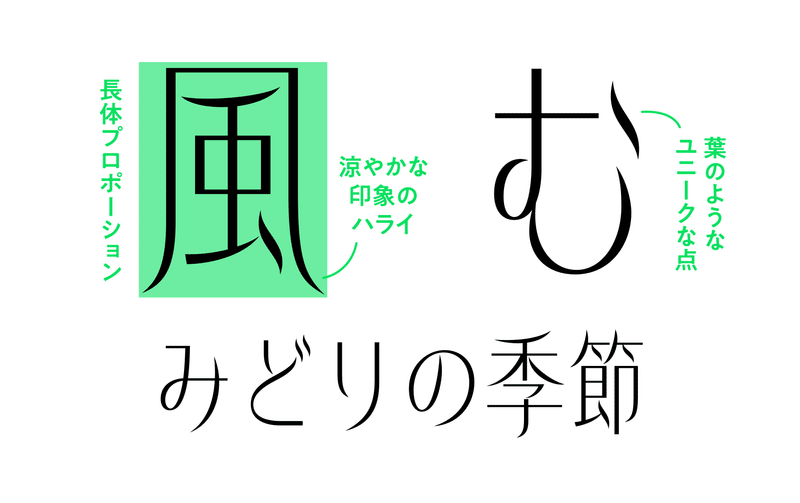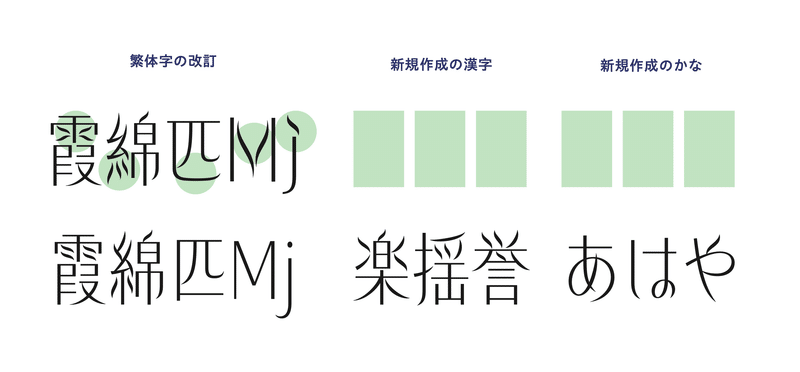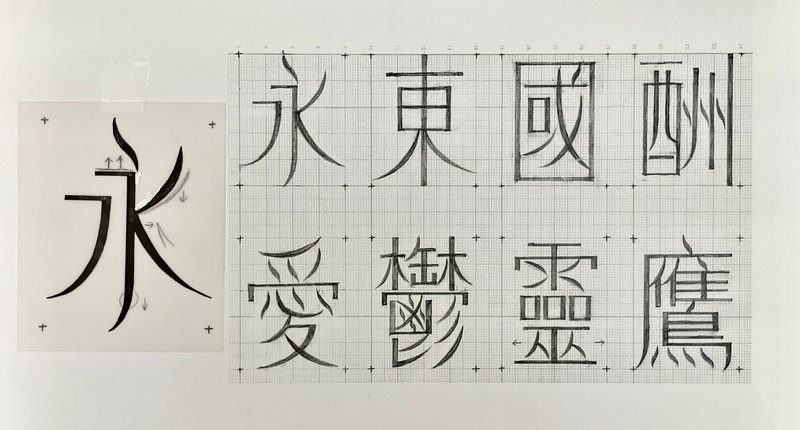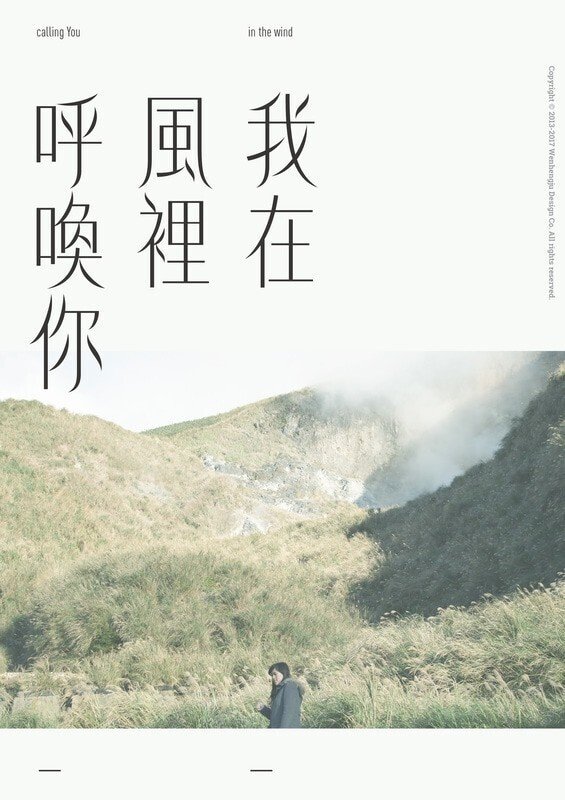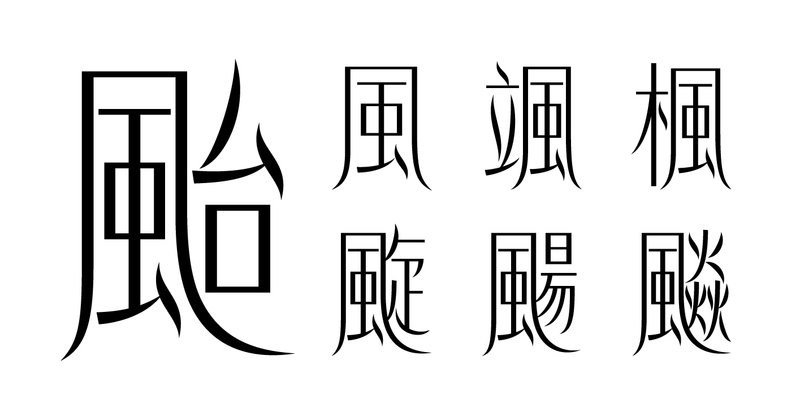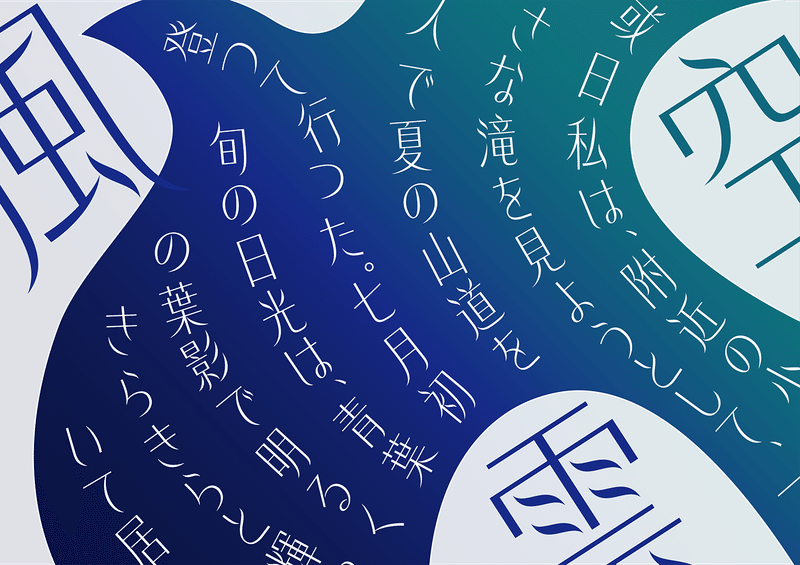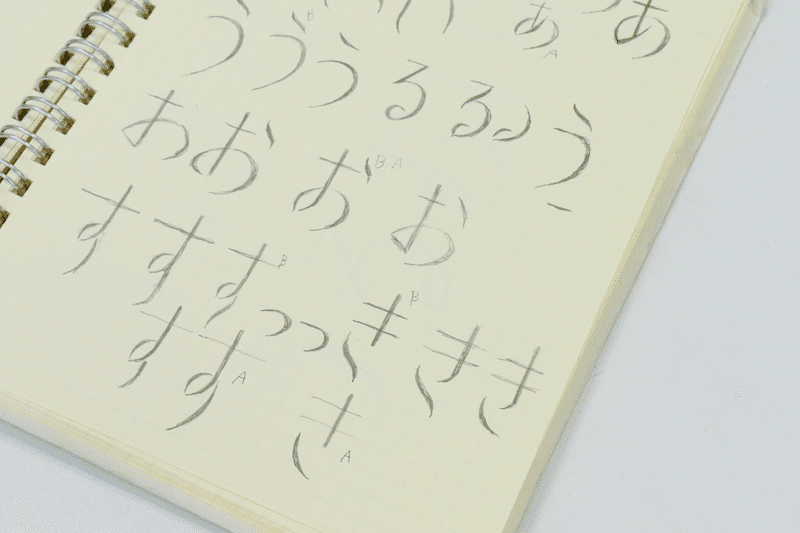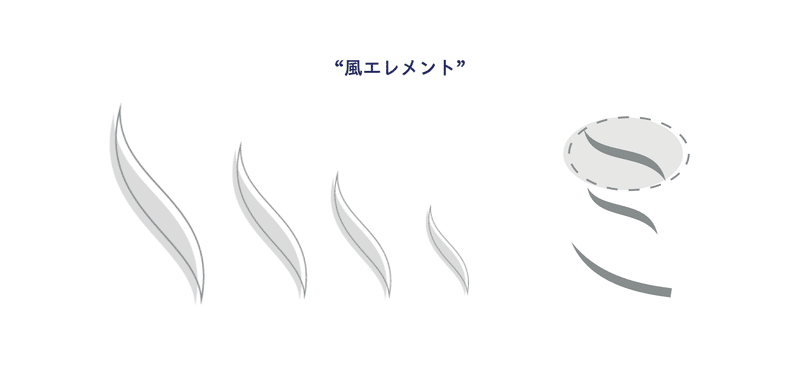
台湾の風薫るデザイン書体「美風」
突然ですが、次の文章を見て何か気づくことはありませんか?
どちらも日本語で書かれていますが、上のフォントには繁体字書体、下のフォントには和文書体が使われています。
中国語の文章を見たときに一見知っている漢字でも書き方が違うように感じたことがあるかもしれませんが、このように比べてみると「風」「色彩」など、和文書体と同じ形の文字があるのがわかりますよね。
今回は、そんな和文とも共通点のある繁体字から制作された和文書体「美風」を紹介します。
美風の紹介
デザインの特徴
美風はその名にあるように、風、舞い落ちる葉、揺れるススキなど自然をモチーフにして設計されたデザイン書体です。
よく見ると「風」や「む」の点画が葉っぱのようなデザインになっています。
長体な骨格と繊細でシャープなラインが特徴で、水平垂直に整備された縦画・横画と、ハライや点画に見られる滑らかな曲線のエレメントの組み合わせが、涼やかで洗練された印象を与えます。
美風は2023年の新書体としてリリースされた和文書体ですが、台湾のデザイン事務所「玉川設計所」が手掛ける繁体字フォント「風體 Wind Font」をベースに制作しています。
美風の開発背景
日本からアクセスも良いことから、モリサワでは台湾で定期的なトレンドリサーチを行っていて、そのなかで風體と出会いました。斬新で優雅なデザインに加え、台湾の自然に着目した書体コンセプトが決め手となり、作者に共同制作の話を持ち出す形で美風の開発はスタートしました。
繁体字書体も和文書体も共通する漢字を使うことがありますが、繁体字の字形だと日本では見慣れない形になっているケースや、和文書体でしか使わない漢字も存在します。そのため、今回は玉川設計所に漢字制作を協力いただき、日本特有のひらがなやカタカナはモリサワで新規作成することとなりました。
ここからはオリジナル書体「風體」の作者である玉川設計所のWenさんと、和文版書体「美風」の作者であるモリサワの吉村さんにインタビューを行い、風體から美風が誕生した経緯に迫ります。
自然と文字が融合する繁体字書体「風體」
台湾現地の国立大学の視覚デザインコース卒業後、2013年よりグラフィックデザイン兼タイプファウンダリ「玉川設計所」を設立。2018年に繁体字書体「風體」、2022年に同じく繁体字書体「拳體」をリリース。それぞれ2019年、2020年にゴールデン・ピン・コンセプトデザイン・アワード賞を受賞し「拳體」は年間特別賞も受賞。
ー 最初にWenさんご自身のことをお聞きしたいのですが、どのようなきっかけで書体デザインに興味をもちましたか?
Wen 小学生から高校生まで書道を続けていたため、自然と文字の造形に関する興味を持ちました。大学ではグラフィックデザインコースを専攻する中で特にロゴデザインを学び、大学院で本格的に文字に関する研究や制作を行いたいと考えいた中で書体デザインに出会いました。風體は大学院での卒業制作になります。
ー 風體の特徴について教えてください。
Wen 風體は、「空気」と関連する作品を制作したくて生まれた書体です。風やそよぐ芒草(イネ科の植物)など自然界の要素を書体デザインに取り入れることがコンセプトになっています。長体な文字のフォルムが優雅な雰囲気を漂わせており、特に見出しに適しています。このフォントの最大の特徴は、茶葉や落葉のような「点」の筆画です。
ー 風體の制作で特にこだわった文字があれば教えてください。
Wen 書体全体を通して可能な限りオリジナリティのあるデザインになるよう一文字一文字制作しました。極端に画数が少なかったり多かったりする文字は苦労しました。特に気を配った文字としてはコンセプトでもある「風」のパーツが入っている文字です。例えば「颱」(繁体字)は工夫しながら作りました。
ー 和文版の美風の開発にはどのように参加されましたか?
Wen 美風は私が主に和文書体に必要な漢字の制作や漢字の改定を担当し、仮名の新規制作や英数字の改定はモリサワさんのデザイナーが担当するという分業で共同制作されました。日本の漢字と台湾の繁体漢字では書き方と筆画の微細な違いがあるため、注意を払う必要がありました。そのほか、モリサワのタイプデザイナーである吉村さんの協力のもと、部首パーツの筆画の統一や見直しを行いました。モリサワチームのご協力には本当に感謝しており、和文書体として完成した美風は非常に美しく、とても気に入っています。
風體の香りを残しつつ和文らしさを求めた「美風」
愛知県立芸術大学(デザイン・工芸科 デザイン専攻)卒業後、2015年モリサワ文研に入社。2017年モリサワに転属。 「Clarimo UD PE」、「UD新ゴ(AP版)」欧文関連、「赤のアリス」、「オズ」等の開発・拡張に携わる。最近の好きな書体は「秀英丸ゴシック」。
美風にもそよ風の雰囲気を演出したい
ー 美風は台湾のWenさんとの共同開発ではどのようにしてコミュニケーションをとっていましたか?
吉村 顔を合わせたのは初回のオンライン会議1回のみでした。あとはずっとチャットでやり取りをしていましたが、コミュニケーションが取りやすく、なによりレスポンスが早くて作業しやすかったです。
ー 繁体字に搭載されていない仮名は新規で作成だったと思いますが、制作をどのように進めましたか?
吉村 漢字自体は大きく変えないことが大前提だったので、美風らしいちょうどいい抜け感について結構悩みました。
最初は漢字のエレメントを組み合わせて仮名を作ってみたのですが、抜け感が増えるとかえって漢字と合わなくなってしまって。文章を組んだ時も、白い部分がチラついて漢字の邪魔をしているように感じました。
初めて風體を見た時、おしとやかにそよそよ風がなびいている印象を受けたので、抜けすぎてしまった部分を繋いで、よりシンプルなデザインに修正しました。
そのため最終的には線を全て離すのではなく、繋げるところは繋げて、抜け感を出したいところは離すデザインにしました。
ー 具体的にどういうところで抜け感を出しましたか?
吉村 例えばひらがなの「む」は、全部繋げたデザインだと見た目が硬い印象になってしまい、一部だけ線を離しました。他にも文字全体を見たときの濃度(黒さ加減)を調整するために抜け感を作ることもありました。
ー お気に入りの文字はありますか?
吉村 カタカナの「ミ」が気に入っています。最初3本の線をどうしようかなと思ったんですけど風っぽい雰囲気を演出できたと思います。チームでは「ミ」の線に見られるようなデザインを “風エレメント” と呼んでいました。
ー 制作が難しかった文字はありますか?
吉村 風體と同じく美風も長体書体のため、いくつか幅の調整に悩んだ文字があります。
例えば横に広がるような「ね」「れ」「お」、エレメントが分かれている「け」「は」「ほ」などは真ん中に寄せると窮屈な印象になってしまい、調整が大変でした。
他にも長体に関して、「○」「▲」「□」「☀︎」などの記号も縦に引き伸ばされてしまったり、潰されてしまったりしている感を出したくなくて、「最初から私はこういう形ですよ」と言っているようなデザインにするのが難しかったです。
ー 欧文はどういうところにこだわって作成しましたか?
吉村 オリジナルの風體にはすでに欧文が入っていましたが、日本語のように漢字・かな・英数字全てが混ざった文章の中だと、欧文の個性が際立ってしまい読みにくい印象がありました。なので、よりシンプルで読みやすいデザインに変更しました。さらに欧文に合わせて、元々入っていた記号類も変更しました。
欧文は「m」や「p」など、抜け感がいいなと思ったオリジナルのデザインを参考にして制作しました。
風體で見られるデザインの要素を減らしたり増やしたりながら、かなを含めた和欧混植の文章でも使いやすいデザインにしました。
和文らしい字形の追求
ー 漢字の制作はどのように進めましたか?
吉村 まずチームで繁体字と和文のコード対応表を作成して、どの文字が対応しているかを調べました。そしてそれを元に字形の違いを調査して、修正する・しないの線引きをしていきました。
繁体字の文字セットの中で日本語と同じ字体の文字もあれば、違う字体の文字もあります。日本で一般的に使っているシンプルな字体の漢字(新字体)が繁体字の文字セットにはなかったり、繁体字の複雑な字体の漢字(旧字体)が今回扱う和文の文字セットには入ってないこともありました。結果的に、Wenさんにはかなりの文字数の作成を依頼しましたね。
赤:新規作成、黄:一部修正、緑:オリジナルのまま
ー Wenさんにはどのように漢字の字形変更を依頼したのでしょうか?
吉村 主に活字の字形に合わせるよう変更をお願いしました。今の和文書体は明朝体活字などに由来する字形ですが、繁体字は書道で書くような字形になっています。例えば筆書体とほぼ同じ形の、例えば漢字の「糸」は縦線に点が2つですが、書き文字だと点が3つになります。「糸」は1画目も変更したので、同じように「玄」の3画目も変更しています。
筆書体なら繁体字の字形のままでもあまり違和感はないのですが、普段よく使うフォントだと日本人の感覚としては読みづらいと思ったので、Wenさんには日本人が読みやすい字形になるよう修正してもらいました。
活字の参考字形(右下):リュウミン
ただ、誤字ではなく、読めないわけでもないので、一部で美風らしいデザインを残したものもあり、全て修正したわけではありません。
例えば “亠” や “豕” などは活字由来ではない書き方ですが、美風らしさがあるので、そのまま採用しました。
思い返すとどこを変えてもらうか決めることが大変でしたね。開発中は繁体字の勉強もしながら修正ラインを決めていきました。
ー 「美風」はどんなシーンで活躍しそうな書体でしょうか?
吉村 化粧品や衛生用品など、清潔感のある製品で洗練・上品といった印象のフォントをよく見かけるので、美風もこういうシーンで使われるようになったらいいな、と思いながら制作しました。
エレメントだけ見ると個性が強そうですが、グラフィックデザイナーさんが手を加える余地がある書体デザインだと思うので、ロゴなどでの利用にも期待しています。
台湾で生まれた書体「風體」と、そのルーツを持つ和文書体の「美風」。
1つの “風” が日本に伝わり、その “風” がただそのまま使われるのではなく、オリジナルをリスペクトしつつ、その風土に合わせてデザインされていましたね。
繁体字をもとに自然な形でデザインされた美風をぜひいろんな場面で使っていただきたいです。